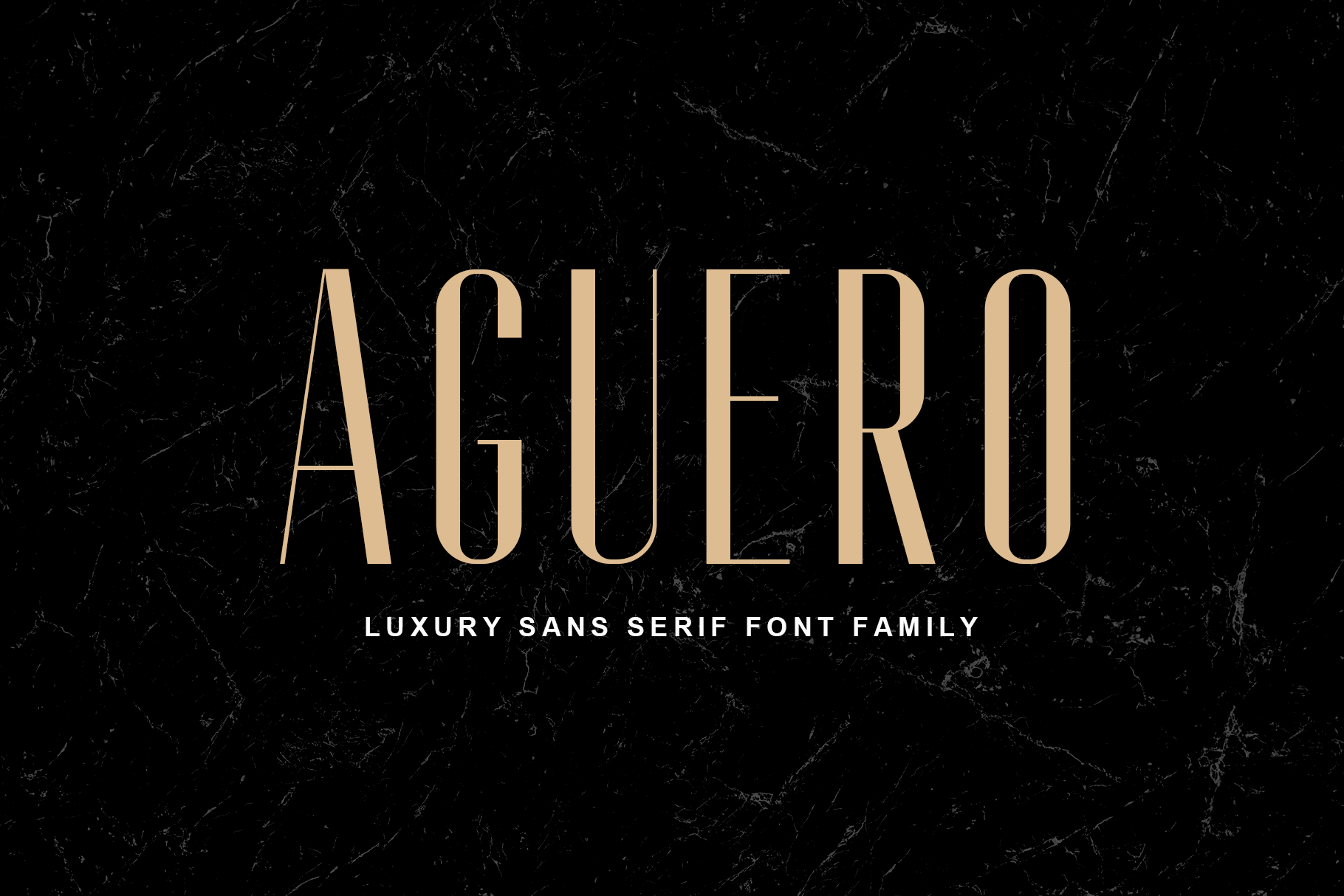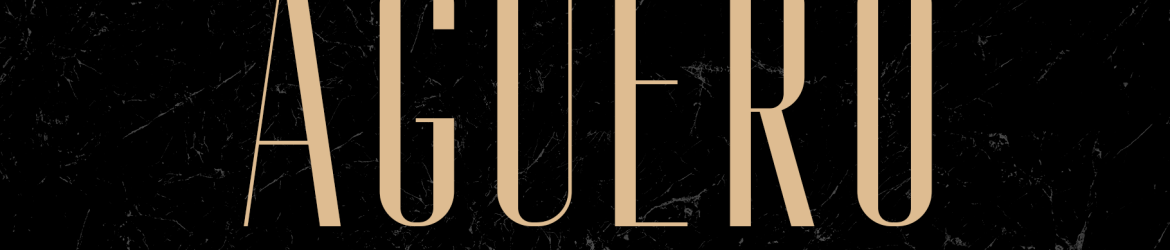
Aguero Font – Download Grátis
Aguero Font é uma elegante e autêntica família de tipo gíria sem serif criada pela Craft Supply Co., ideal para aqueles que buscam simplicidade e modernidade em seus projetos visuais. Se destacando pela característica do baixo contraste nos traços, esta fonte mantém um toque minimalista em suas formas redondas de caracteres. Além disso, seu estilo firme e limpo se adequa perfeitamente para aplicações que exigem simplicidade na apresentação visual, como logos ou materiais de marketing. Esta família de type é uma escolha ideal tanto para designers digitais quanto para profissionais da impressão, pois oferece a combinação necessária de elegância e simplicidade perfeita para criar um design moderno e sofisticado.